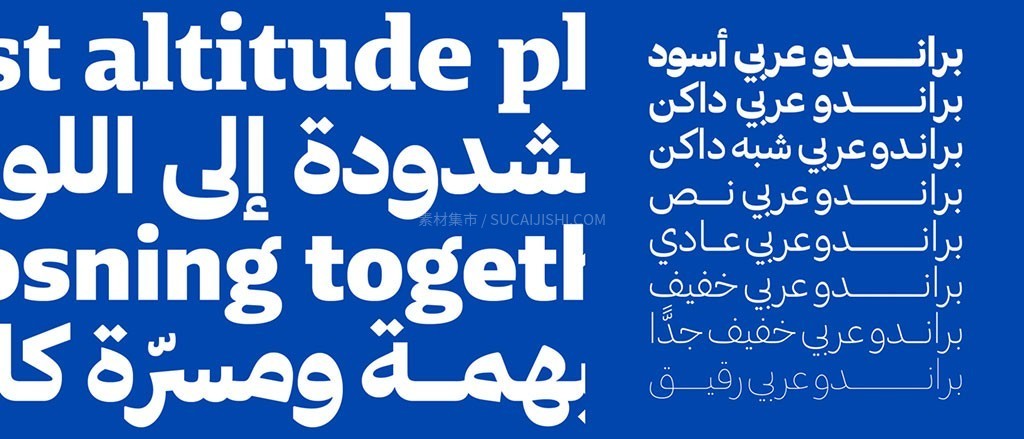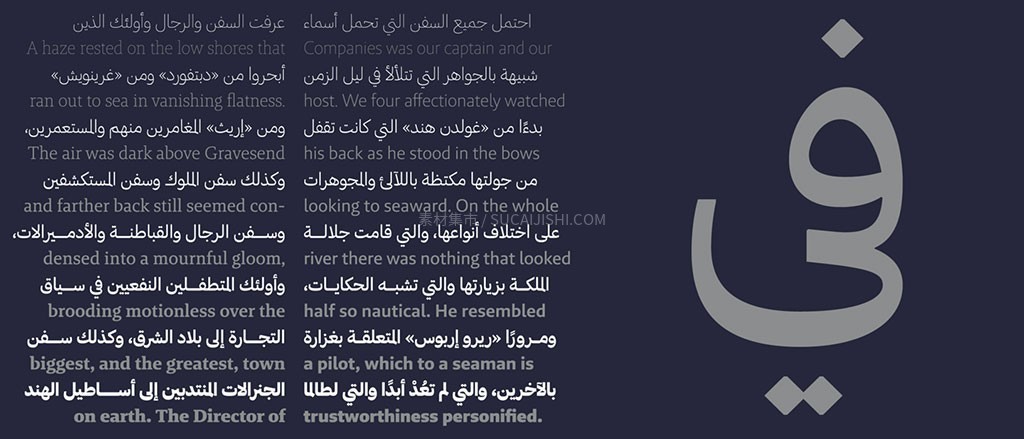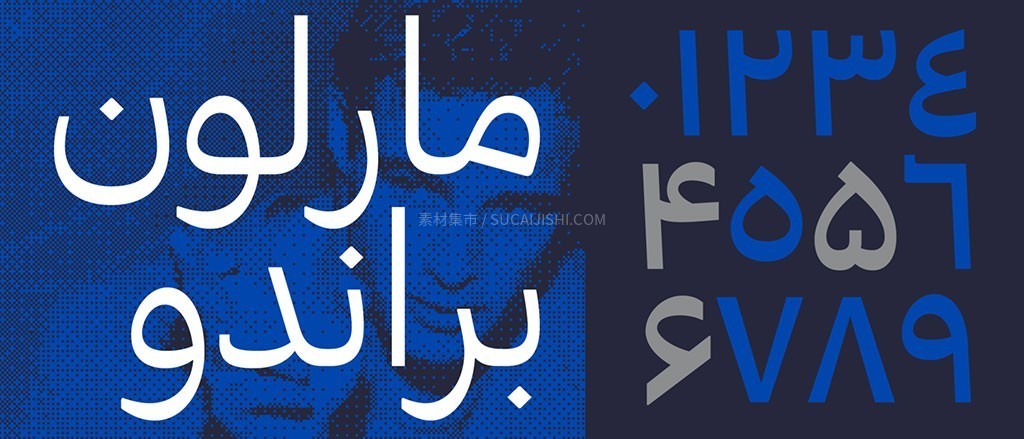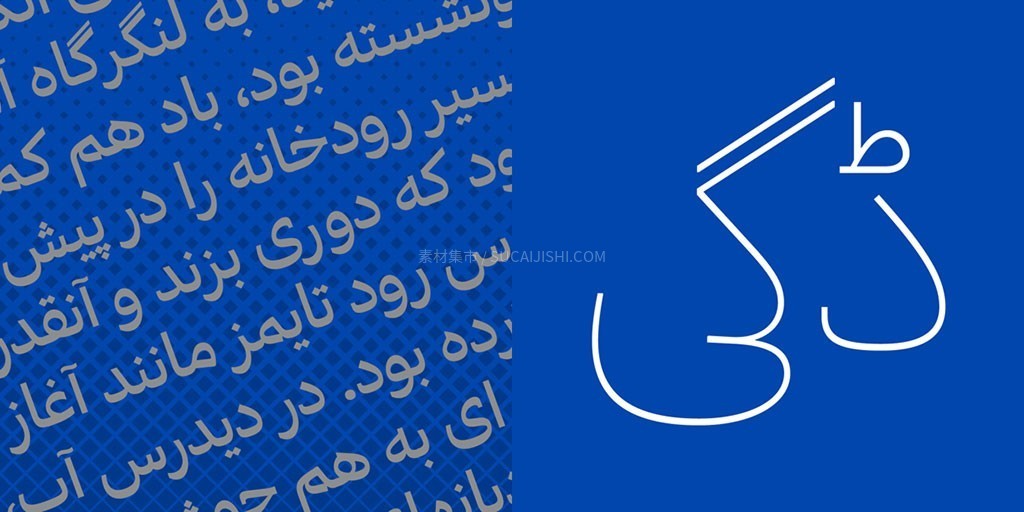
Brando Arabic 阿拉伯语字体家族 (全套24款)
Brando Arabic 是对 Mike Abbink 设计的经典 Brando 拉丁文字体的深度诠释。它完美融合了硬朗的几何结构与柔和的纳斯赫体 (Naskh) 书法艺术,在遵循阿拉伯语传统书写惯例的同时,赋予了文字现代、精致且优雅的视觉气质。